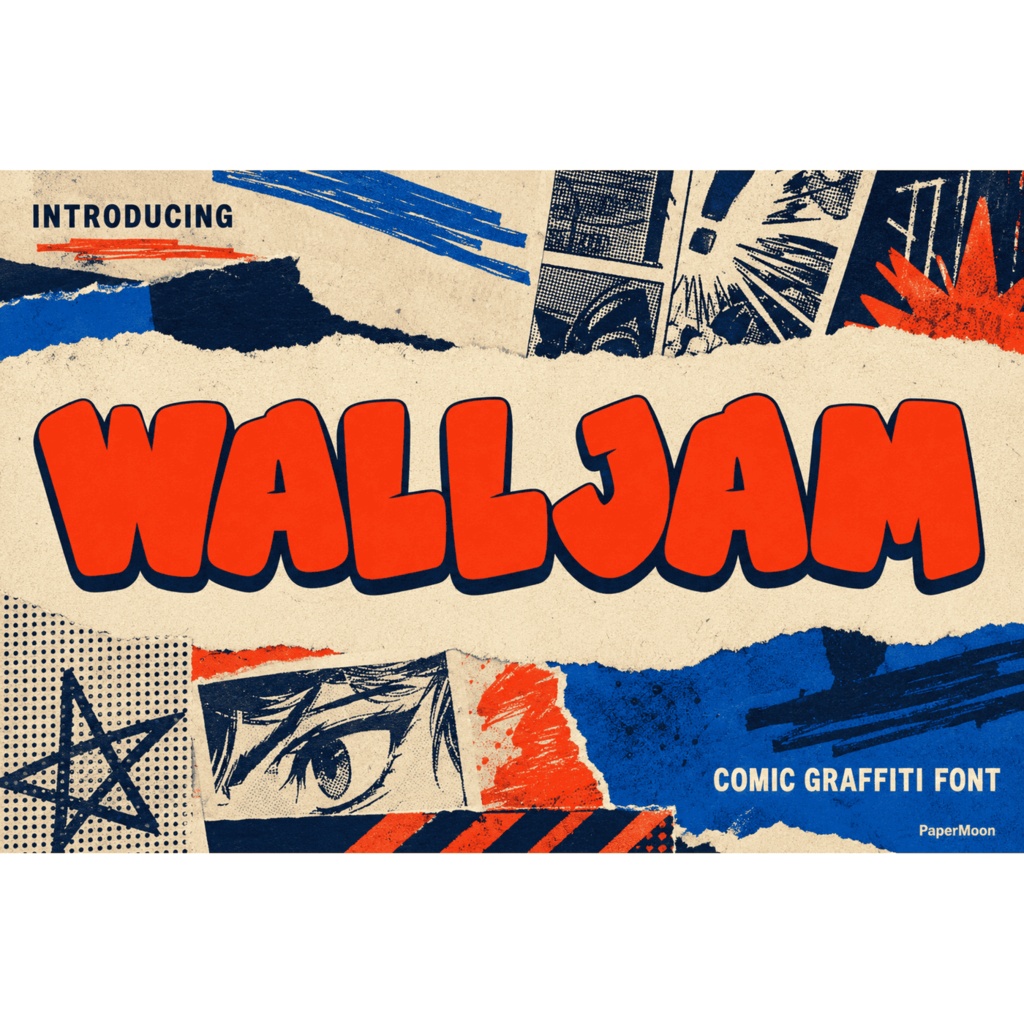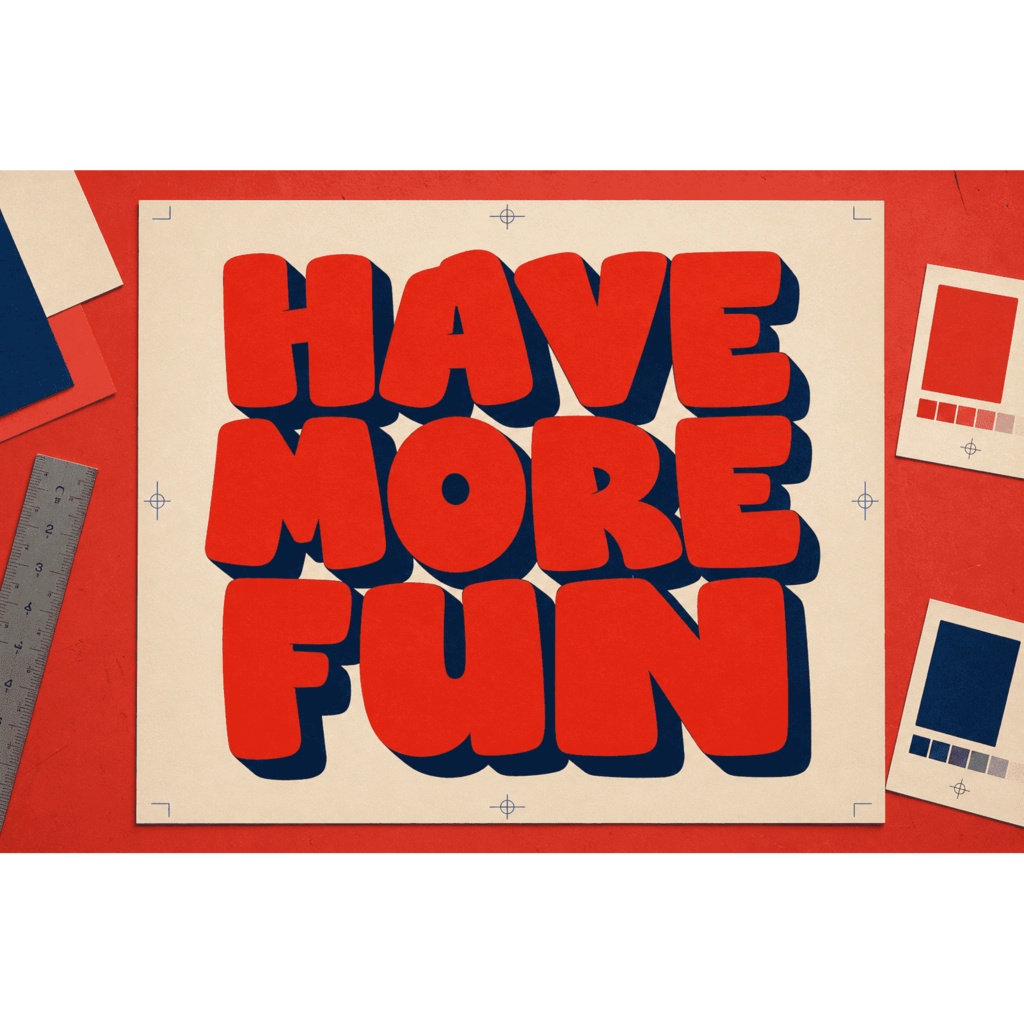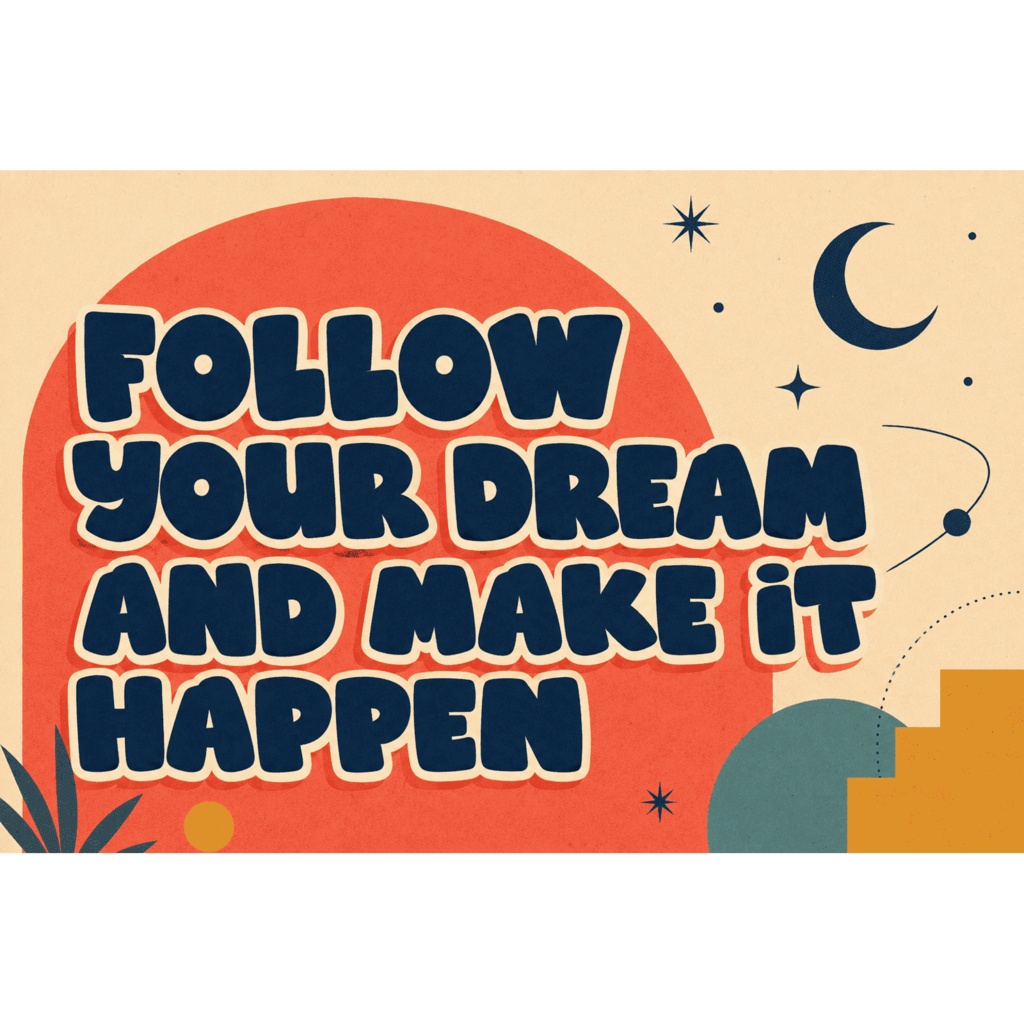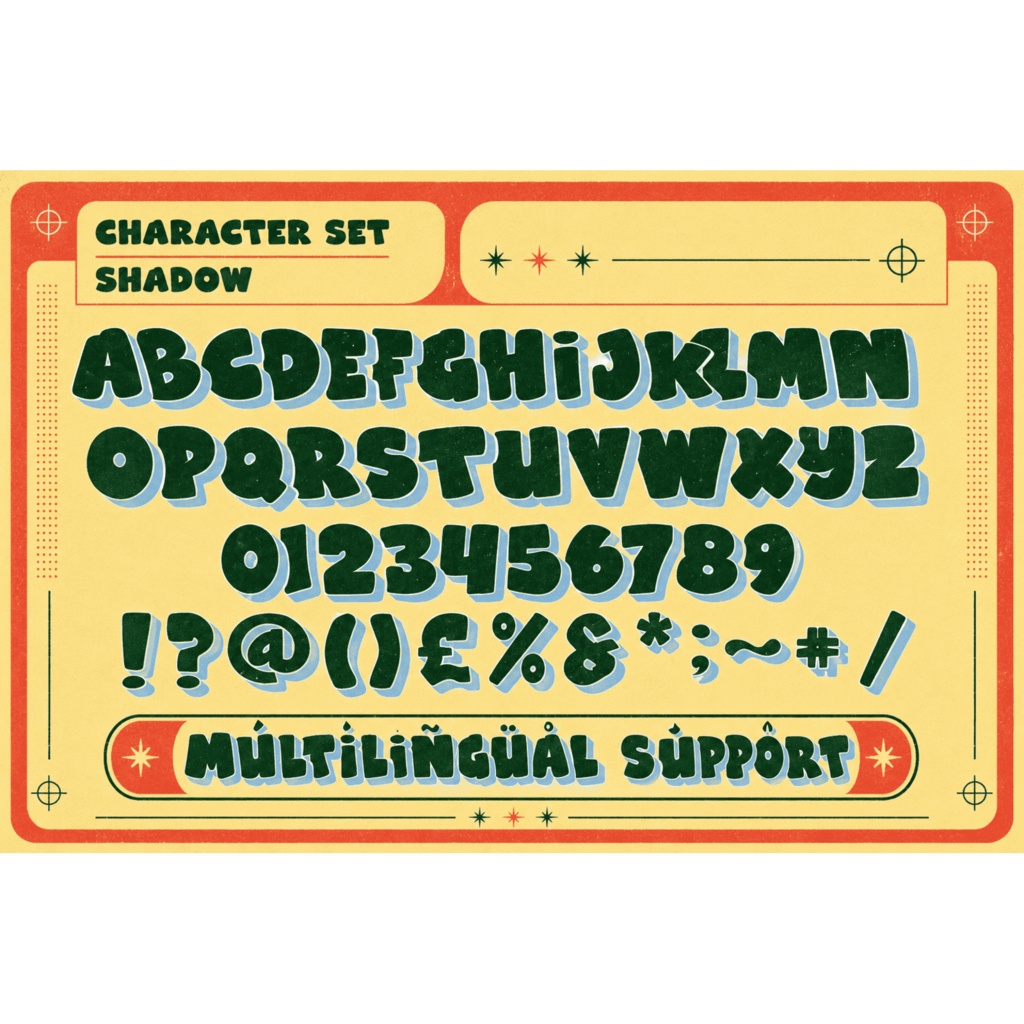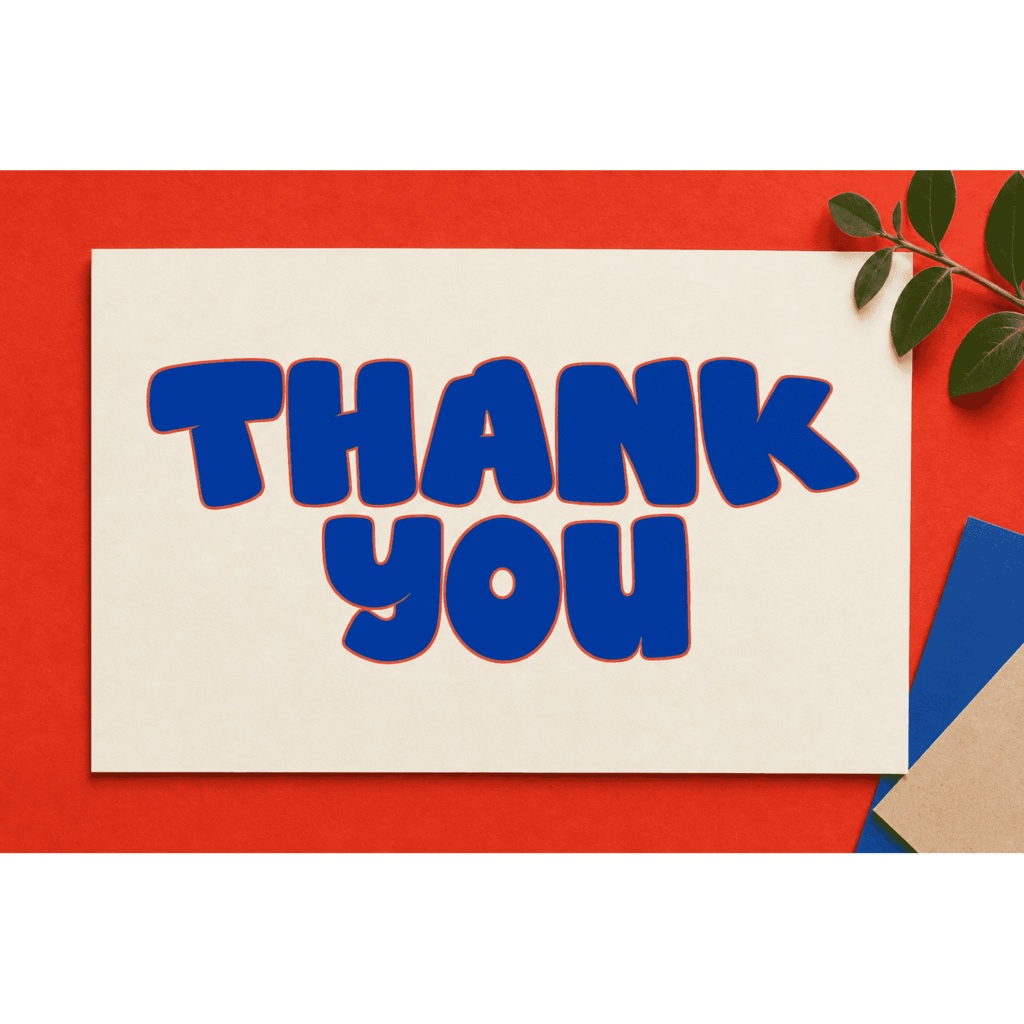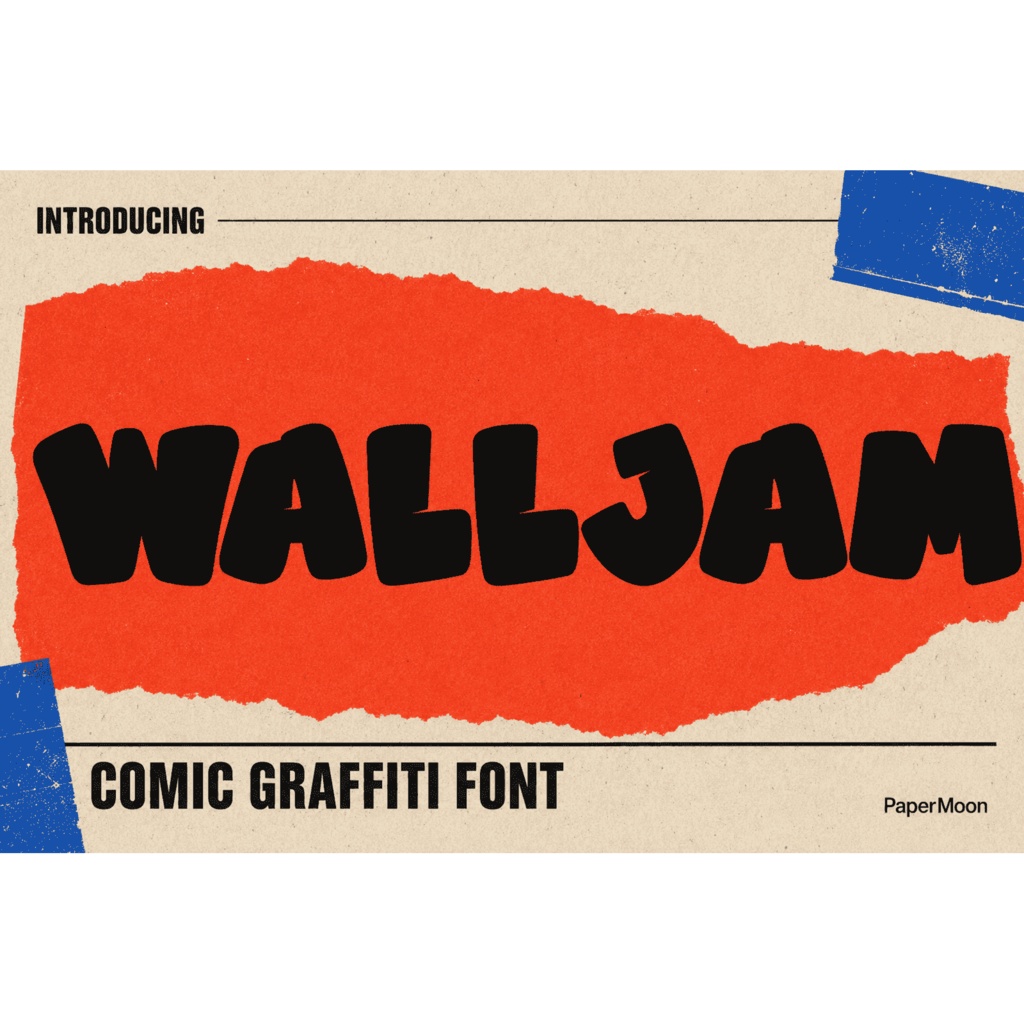
WallJam | グラフィティ欧文フォント2書体セット | Comic Graffiti Font Duo
WallJamは、ストリートアート風のコミックグラフィティ欧文フォント2書体セット(Font Duo)です。手描きのような太くて元気なラインと、漫画のようなポップなエネルギーを持ったディスプレイ向けの英字フォントで、ポスター、ステッカー、ストリートウェア、ゲーム系グラフィック、サムネイルなど、存在感のあるタイトル文字を作りたいときに活躍します。迫力はありながら攻撃的すぎず、子ども向けデザインや遊び心のあるブランディングにも使いやすい書体です。 収録内容 / Included ・ WallJam(Regular): インパクトのある太字ベース。手描きらしい表情で見出しを力強く見せます。 ・ WallJam Shadow: 同じ文字に3Dドロップシャドウを内蔵。1パスで立体的な文字が作れ、装飾レイヤーを組まずに奥行きを出せます。 対応文字 / Character Set 各スタイルとも236グリフを収録。Basic Latin(英字の大文字・小文字)、Latin-1 Supplement、西ヨーロッパ圏の句読点・記号に加え、よく使う算術記号・通貨記号、№、™に対応しています。OpenTypeのGSUB合字(fi、fl)とGPOSカーニングも含まれます。 注意: 本フォントはラテン文字(英語・西ヨーロッパ言語)専用です。日本語の文字(ひらがな・カタカナ・漢字)は収録されておらず、PUAエンコードでもありません。 用途 / Uses 子ども向けプロジェクト、遊び心のあるブランディング、ポスター、ステッカー、ストリートウェア、ゲームタイトル・HUD、YouTubeサムネイル、ロゴワードマークなどにおすすめです。 形式 / Formats 各スタイルをOTF、TTF、WOFF、WOFF2の4形式で収録(計8ファイル)。デスクトップ用途にはOTF/TTFを、Web用途にはWOFF/WOFF2をご利用ください。 対応環境 / Compatibility Mac / PC対応。インストール可能な埋め込み(fsType 0)のため、Adobe Illustrator、Adobe Photoshop、Corel Draw、Procreateなど標準的なフォント環境で利用できます。インストール後はアプリケーションを再起動し、WallJamまたはWallJam Shadowをフォントメニューから選択してください。合字・カーニングはOpenType機能に対応したアプリケーションで有効になります。 利用許諾 / License 購入者は商用利用が可能です(ロゴ、ブランディング、クライアント制作、Tシャツ・マグカップ・プリントなど販売商品、SNS、Web・アプリデザイン)。フォントファイル自体の再配布・再販・転売は禁止です。最終的なライセンス条件は出品時にBOOTHで設定する本文に従ってください。拡張ライセンスが必要な場合は tankisompela010@gmail.com へお問い合わせください。 注意 / Note プロモーション画像に写るモックアップや装飾グラフィック、ストック素材はフォント本体に含まれません。